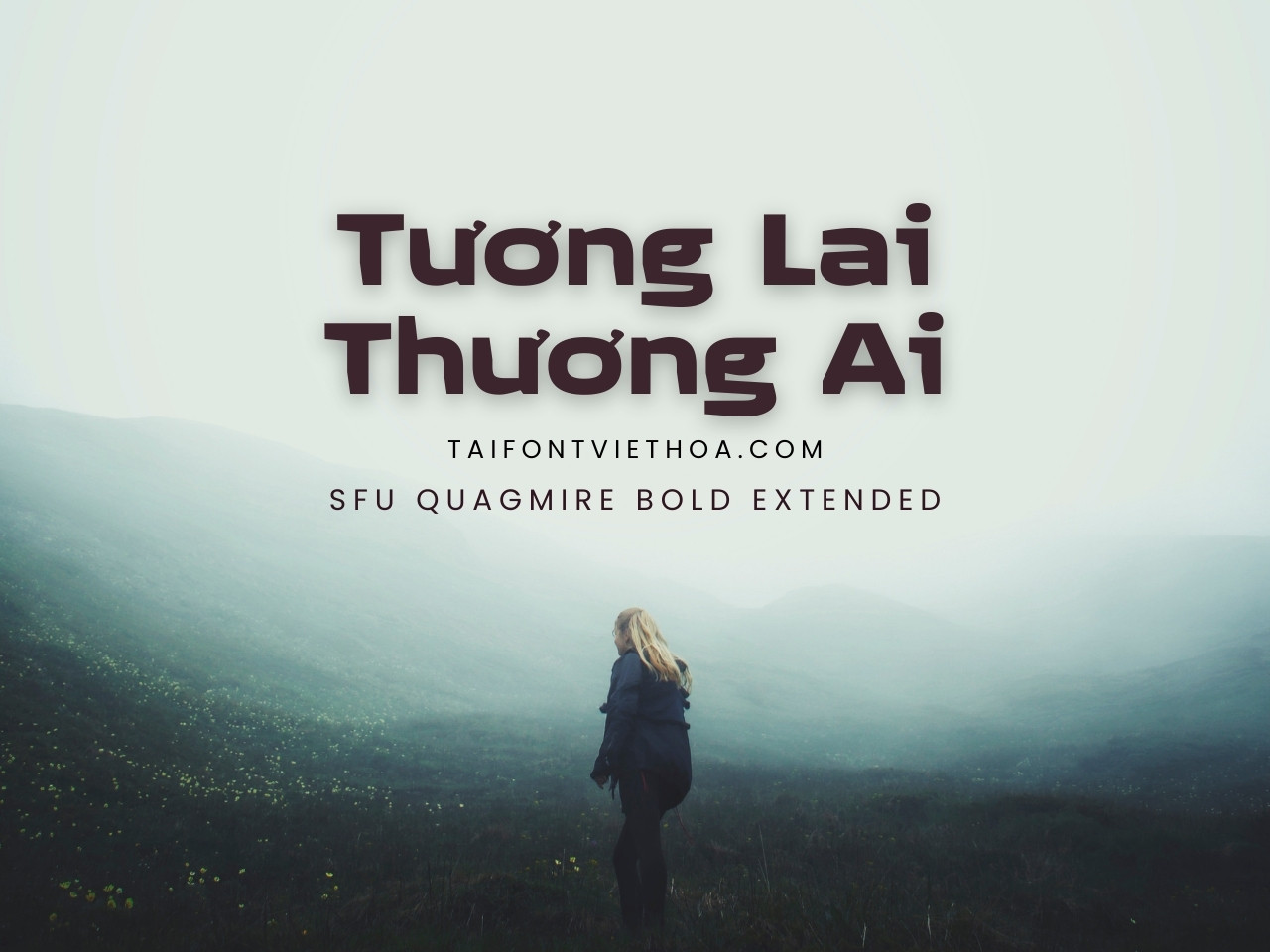
Khám phá SFU Quagmire – Font display đậm chất viễn tưởng và mạnh mẽ
SFU Quagmire là bản Việt hóa của font chữ Quagmire – một thiết kế ấn tượng trong nhóm display, thường được ứng dụng cho các dự án mang phong cách khoa học viễn tưởng, hành động hoặc công nghệ tương lai. Font có đường nét cứng cáp, tạo hình chữ cái đặc trưng với góc cạnh sắc nét và nhấn mạnh sự mạnh mẽ, cá tính. Bản Việt hóa do nhóm SFU thực hiện đã tích hợp đầy đủ dấu tiếng Việt, hỗ trợ hơn 80 ngôn ngữ khác và đảm bảo tính tương thích cao cho các ứng dụng thiết kế tại Việt Nam.
Font Quagmire sau khi được Việt hóa đã được đội ngũ taifontviethoa.com sưu tầm, kiểm tra và ứng dụng trong thực tế nhằm phục vụ cộng đồng thiết kế sáng tạo. Từ các dự án branding cá tính, poster phim, đến các mẫu in ấn sự kiện mang phong cách điện ảnh hoặc công nghệ cao, SFU Quagmire là lựa chọn độc đáo giúp tạo điểm nhấn mạnh mẽ về mặt thị giác.
Đặc điểm thiết kế và tính ứng dụng của SFU Quagmire
SFU Quagmire sở hữu cấu trúc chữ độc đáo với các nét thẳng và góc nhọn, thể hiện phong cách táo bạo, hiện đại và có phần “futuristic”. Với độ đậm vừa phải và các ký tự được tạo hình sáng tạo, font này dễ dàng thu hút sự chú ý và tạo ấn tượng ngay từ cái nhìn đầu tiên. Quagmire phát huy hiệu quả cao nhất trong vai trò tiêu đề lớn, poster, banner quảng cáo, bìa sách hoặc giao diện game.
SFU Quagmire phù hợp cho các ngành nghề như công nghệ, quảng cáo, game, giải trí, truyền thông và đặc biệt là các dự án cần khẳng định cá tính mạnh mẽ. Font rất lý tưởng khi sử dụng trong các thương hiệu công nghệ sáng tạo, logo gaming, bảng hiệu sự kiện hoặc tiêu đề kênh YouTube chuyên về điện ảnh, công nghệ và review sản phẩm số.